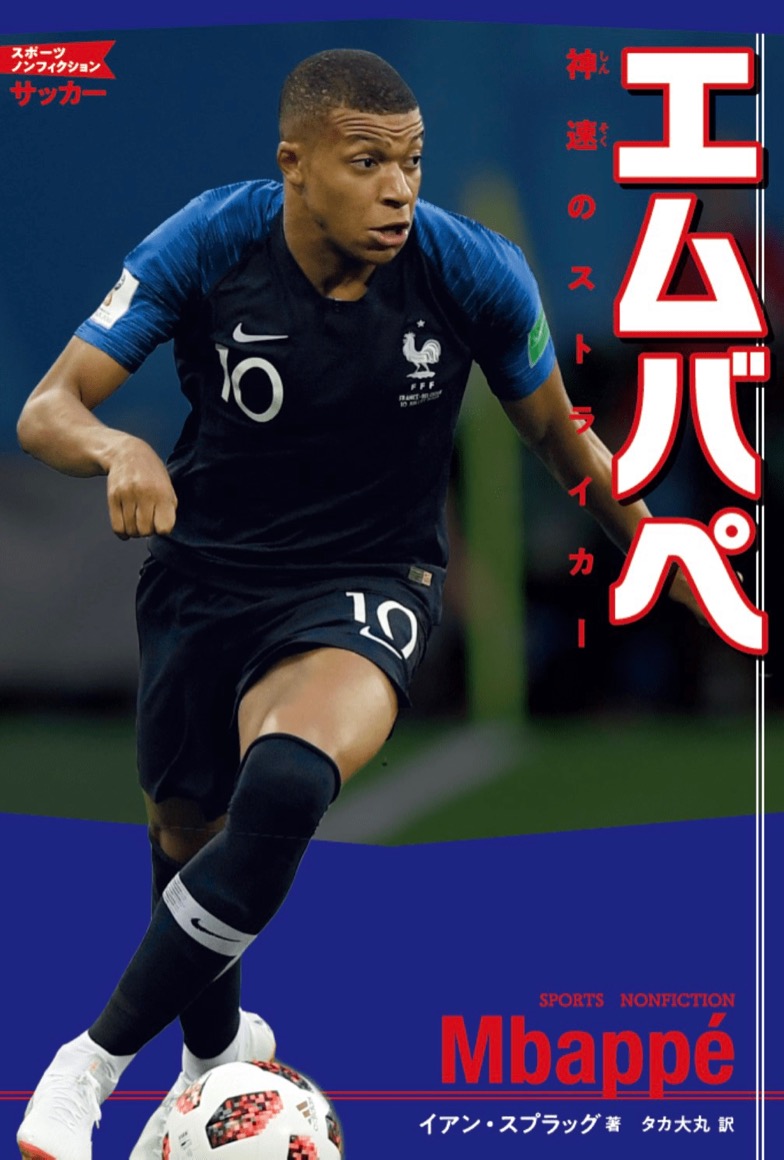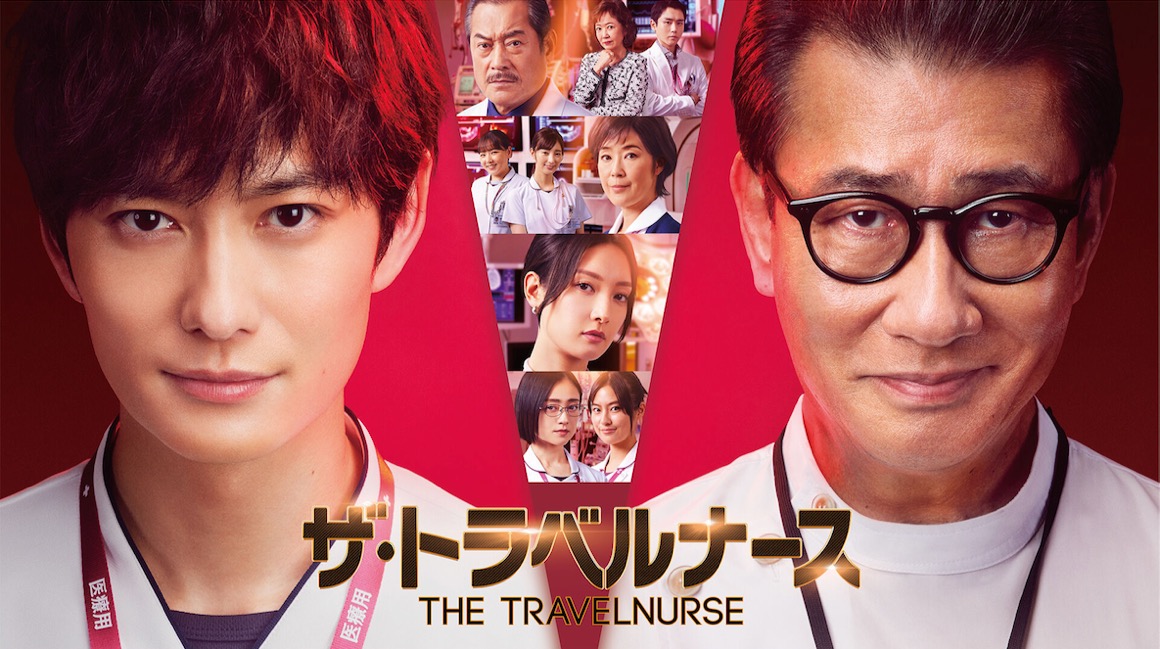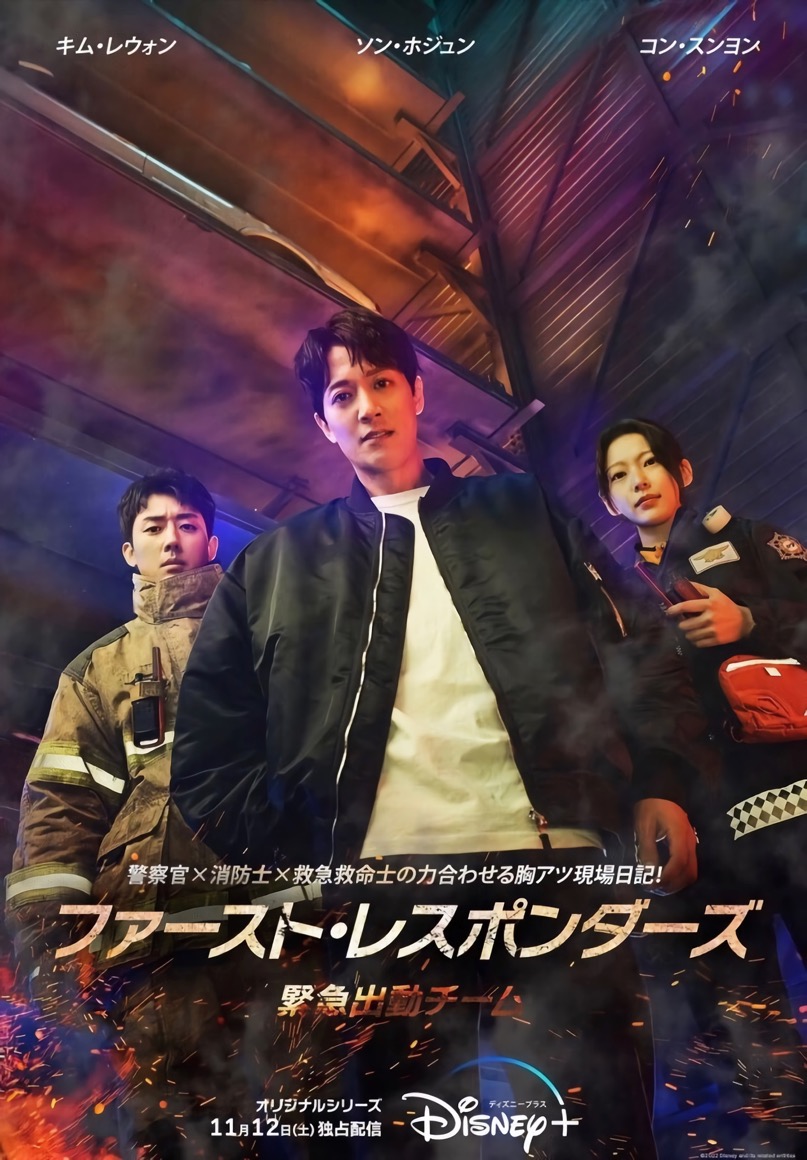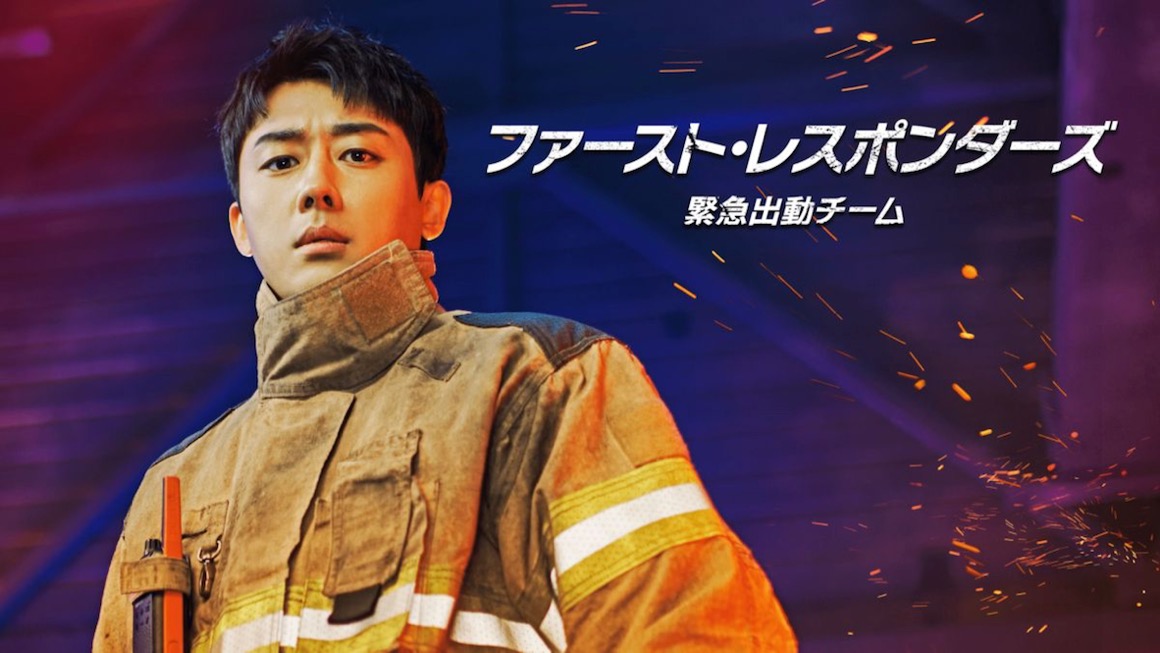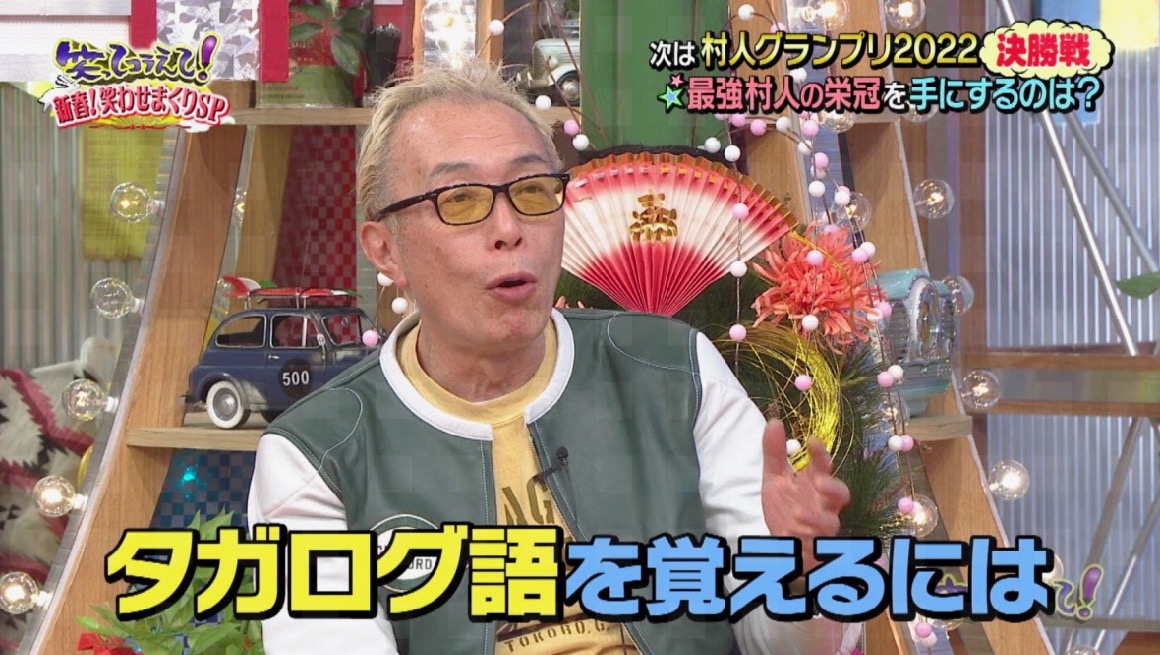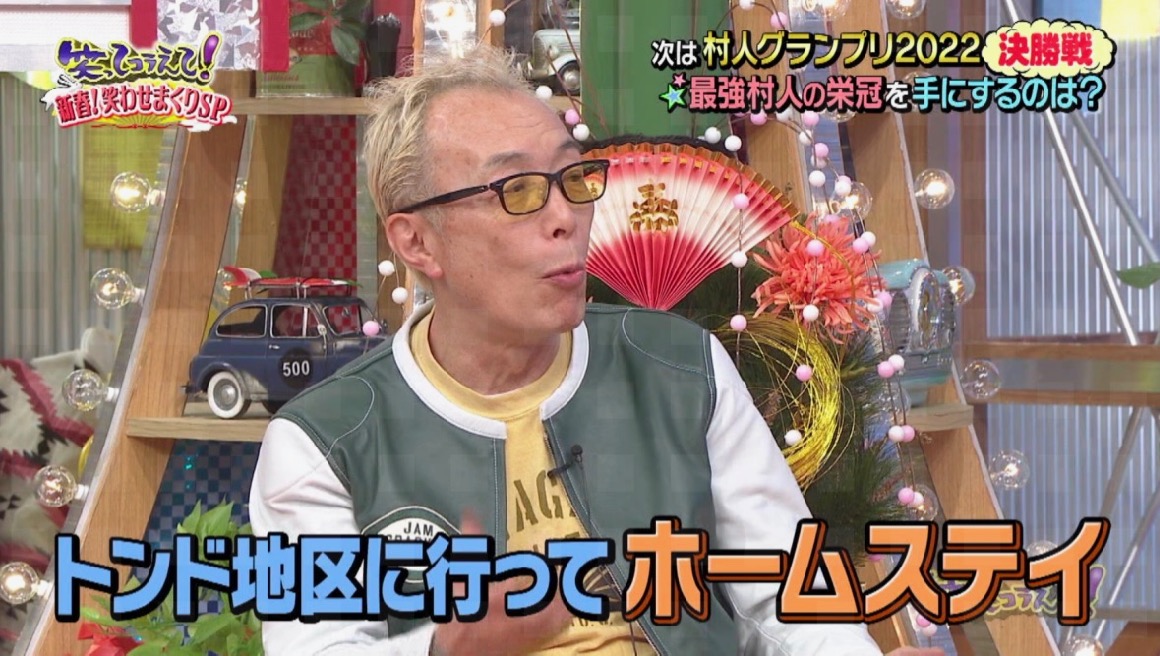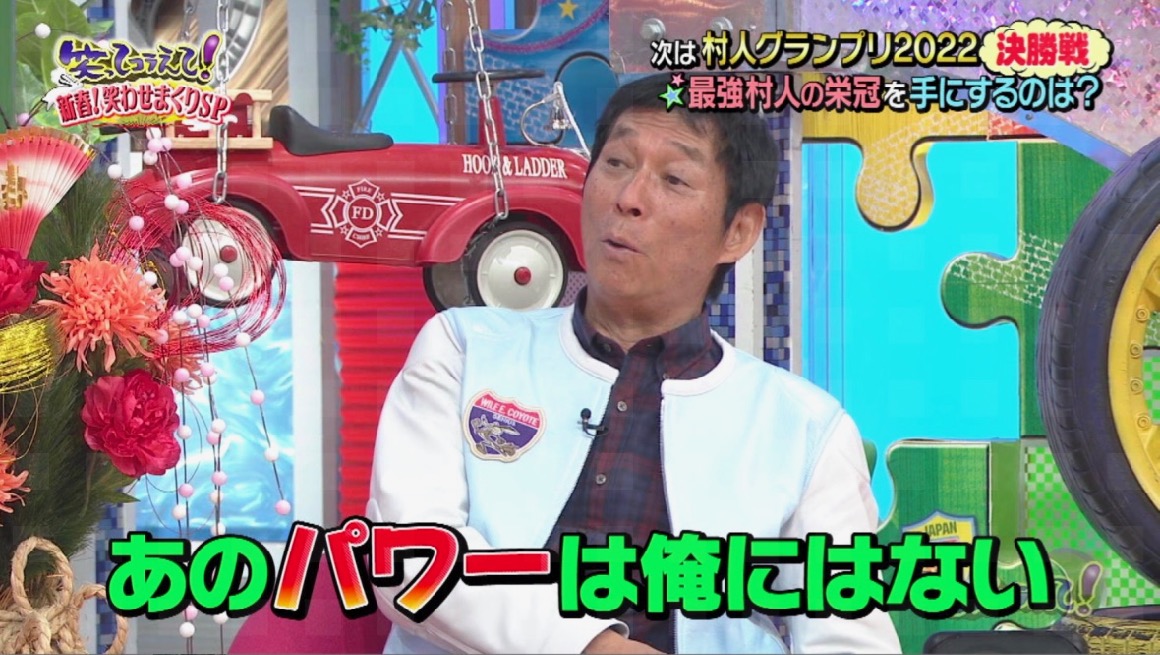
テレビ番組 さとうゆたか
日本テレビ「笑ってコラえて!」。
法律事務所のCM takumi
平松剛法律事務所のCMでF社のニタラゴが使われています。
広告画像 さとうゆたか
日テレの番組 takumi
日テレで放送されている「キントレ」という番組より。
ニタラゴ書体が使われています。
これも…。
マクドナルド さとうゆたか
N.Y.バーガーズってやつ。
あ さとうゆたか
これは、古いやつ。
映画タイトル さとうゆたか
縦型ポスター。
日テレの番組 takumi
日本テレビ「上田と女が吠える夜」より。
最近また、テレビでの使用が増えてきた気がします…。
配信映画タイトル さとうゆたか
横のも。
テレビCM さとうゆたか
自動車共済。
本の表紙 さとうゆたか
書名:オタクの逝き方
著者:メディア・パル
発行:メディア・パル